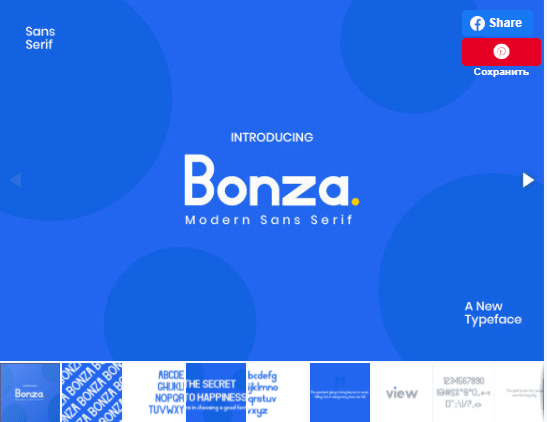
Bonza Font
Bonza - это минималистичный и изящный шрифт без засечек. Его можно легко сопоставить с невероятно большим набором проектов, поэтому добавьте его к своим творческим идеям и обратите внимание, как они выделяются среди них!